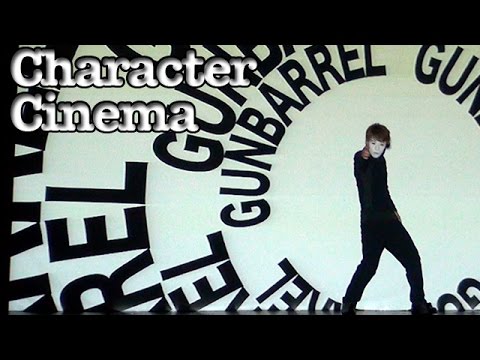
Character Cinema von SIRO-A
Kinofilme aus Typografie
Kinofilme aus Typografie Siro-A_Character-Cinema
SIRO-A sind so etwas wie die japanische Blue Man Group. Mittels Licht-Projektionen, Video-Art und kreativen Body Performances zeigen sie neuartige Formen der Unterhaltung. Eine schöne Variante ist dieses Character Cinema, in dem sie uns allerlei ikonische Filmmotive zeigen, die gänzlich aus Typografien der Sachen bestehen, die sie darstellen. Total umständlich erklärt, daher seht doch einfach selbst!